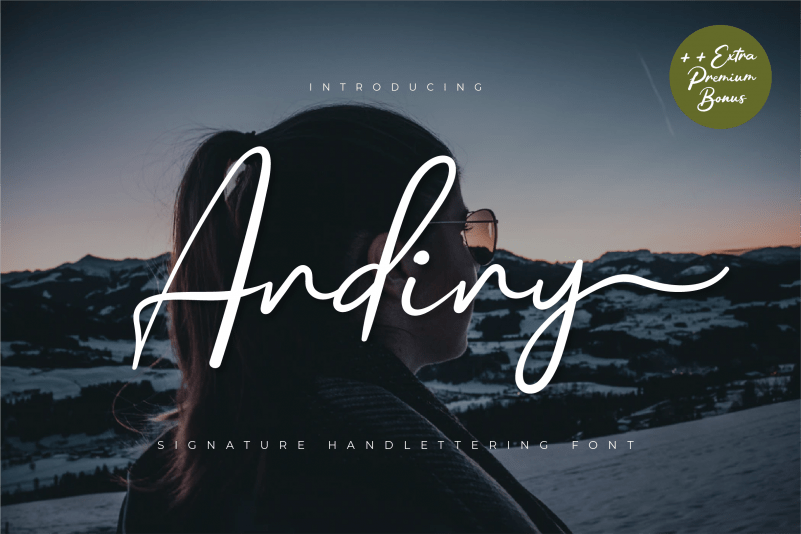
A ‘Andiny Script Font’ é uma elegante tipografia de script feita à mão que transborda a sofisticação do gâmbia com sua frescura contemporânea. Escrevendo e desenhando por completo, essa fonte traz um toque único ao seu design, mantendo os traços estilizados de uma caligrafia clássica enquanto incorpora elementos modernos e inovadores. Perfeita para qualquer projeto que você esteja planejando, seja ele um site pessoal, uma campanha publicitária ou até mesmo um relatório de trabalho, ela o ajudará a chegar ao topo do sucesso. Adquira a ‘Andiny Script Font’ agora e deixe seu estilo se destacar!